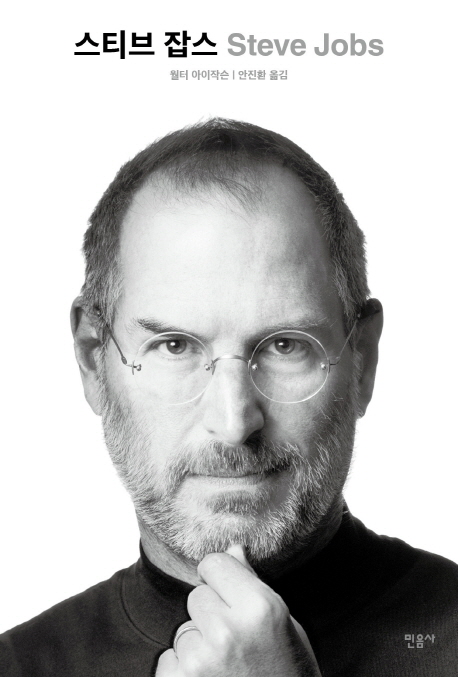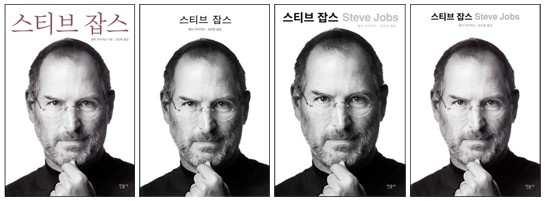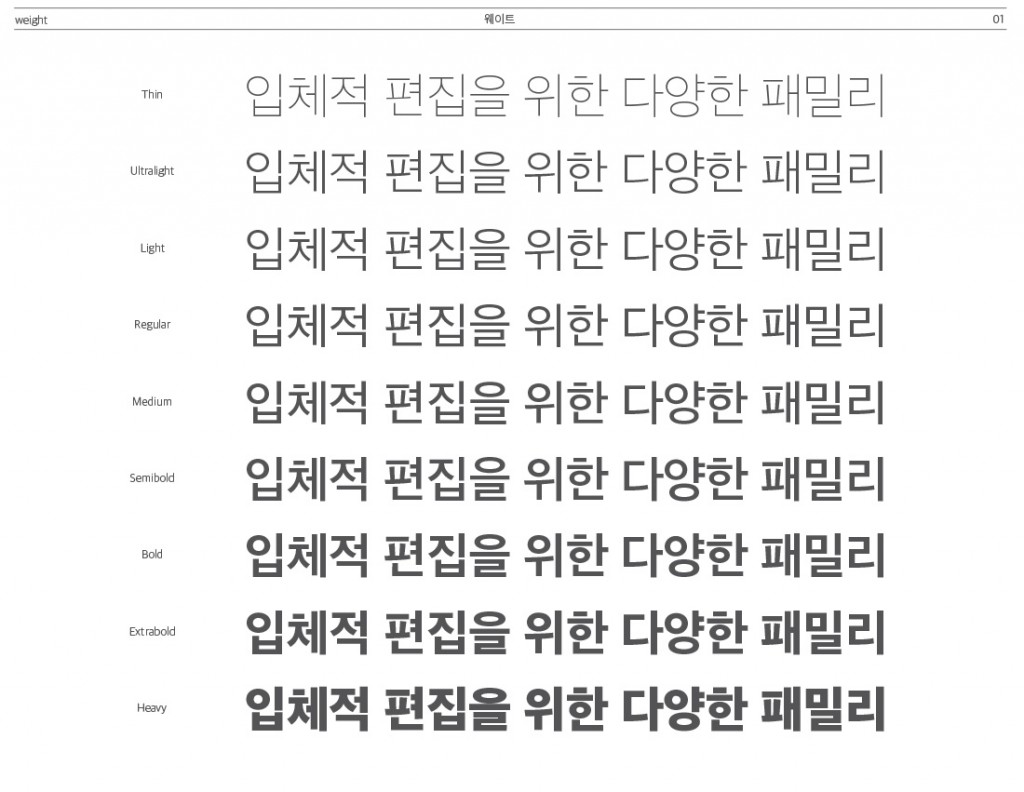
<스티브 잡스> 편집후기 : 스티브 잡스 그리고 산돌고딕Neo
2011년 10월 5일. 전 세계인이 공통으로 기억하는 금세기 몇 안 되는 날짜 중에 하나가 아닐까 싶다. SNS에서, 그리고 전 세계 각지에서 스티브 잡스를 그리워하며 애도했다. 트위터에서는 추모의 글이 넘쳐흘렀고, 애플 매장을 비롯하여 그를 떠올릴 수 있거나 기릴 수 있는 곳이라면 어디든 한 입 베어 문 사과와 추모의 포스트잇이 쌓여 갔다.
“단순함이란 궁극의 정교함이다.”
한국 시각으로 2011년 10월 6일. 그날 아침을 나도 기억한다. 아니, 잊을 수가 없다. 전날 늦게까지 야근을 했던 터라 출근 준비가 평소보다 늦어 서두르던 참이었다. 그런데 들려온 아침 뉴스는……. 쉽게 쓰는 표현으로, 거짓말 같았다. 그전부터 그의 건강이 악화되었다는 소식을 들었고, 여기저기서 우려의 목소리를 들었던 터라 생각지도 못했던 일이라고 할 수는 없었지만, 그럼에도 충분히 급작스러웠고, 그의 팬으로서 충격을 받았다. 순간적으로 멍해지고 슬픔이 몰려왔다.
사실 생각보다 많은 이들이 내게 조심스럽게 물었었다. “만약에 잡스가 책 출간 전에 사망하면 책은 어떻게 될까요?” 한편 잔인하지만 또 한편으로 던질 수밖에 없었던 그들의 질문에 나는 대답할 수 없었다. 그런데 그 결론이 갑자기 저 멀리서 나를 향해 달려오기 시작한 것이다. 팬으로서의 슬픔은 접고, 몇 달 전부터 그의 전기를 준비해 왔던 편집자로서 난 패닉에 빠졌다. 정신을 차리고 그의 마지막 목소리가 담긴 전기를 정말로 잘 내야만 했다.
이미 숨 가쁘게 달려온 터였지만, 많은 이들이 책을 기다리고 있었고 지체할 시간이 없었다. 그리하여 29개국의 편집자가 밤낮 없이 ‘전 세계 동시’에 머리를 쥐어뜯고, 고민하고, 마음을 졸였고, 『스티브 잡스』는 변경된 출간 일자 10월 24일에 마법처럼 ‘전 세계 동시’ 출간되었다.
『스티브 잡스』의 출간 준비를 하면서 가장 고민이 되었던 부분은 잡스도 늘 중요하게 여겼던 디자인이었다. 최종 결과물이 나왔을 때, “바로 이거야!”라는 생각이 들었고 그제야 우리 모두 가슴을 쓸었지만, 의외로 그 고민의 과정은 험난했다.
일단, 『스티브 잡스』가 서점에서 경제경영 분야로 분류될 것이 문제였다. 일반론으로 말할 수는 없지만, 특히 경제경영 분야의 도서 표지들은 대체로 제목이 크고 잘 보이게, 그리고 이미지도 분명하게, 과감한 디자인을 하는 경향이 있다. 그런 시장에서 독자들에게 어필을 하려고 하면서 시장의 법칙을 무시하기란 쉽지 않았다. 담당 디자이너도 스티브 잡스가 추구하는 세련된 감각과 독자에게 분명하게 어필할 수 있는 디자인 사이에서 고민이 많을 수밖에 없었다.
첫 번째 이미지는 우리가 초기에 냈던 시안 중 하나이다. 제목이 분명하게 눈에 띄도록 하는 것이 가장 큰 목적이었다. 하지만 그 목적에만 충실할 뿐, 어딘가 어색하고, 스티브 잡스의 이미지에는 어울리지가 않았다. 그래서 잡스의 정체성을 드러내고자 두 번째 이미지처럼, 당시 애플 제품에서 사용하던 애플고딕체도 시도해 보았지만, 제목이 명확하게 보이지 않아 제목으로 쓰기에는 적당하지 않았다.
제목에 쓰기 좋은 서체를 찾는 것은 쉽지 않았고, 출간일은 점점 다가왔다. 그렇게 애간장이 타던 중 돌파구를 찾기 위해 민음사와 인연이 있던, ㈜산돌커뮤니케이션에 근무하는 서체 디자이너에게 의견을 물었다. 그녀는 마침 애플의 iOS5 베타 6에서 한글 전용 폰트로 채택되었던 폰트가 있다고 했다. 지금은 애플의 정식 한글 서체로 채택되었지만, 당시에는 테스트 중이었던 산돌고딕네오였다. 그녀는 고맙게도 산돌고딕네오로 제목을 잡은 시안을 샘플로 보내 주었다. 위의 세 번째 이미지다. 이 시안을 받았을 때, 우리는 이제야 맞는 길로 들어섰다는 것을 알았다. 편집부에서 서체 자문을 구하고 있을 때, 마침 담당 디자이너도 같은 생각으로 전화를 해 왔으니, 우리는 같은 순간에 정답을 깨달았던 것이다.
네 번째 이미지는 우리가 익히 알고 있는 한국어판 『스티브 잡스』 표지다. 산돌고딕네오 서체를 쓰되 좀 더 세련되게 다듬었다. 어떤 면에서는 파격적인 디자인이었다. 이 정도 책 크기에서 이렇게 제목을 작게 쓰고, 책 뒷면에 카피 한 줄 쓰지 않은 책은 아마 없을 것이다. 하지만 우리는 이 표지 시안을 받아 들었을 때 분명히 깨달았다. 제목을 더 크게 말할 필요도 없고, 이 책이 어떤 책인지 더 설명할 필요도 없다는 것을. 스티브 잡스의 확신에 가득한 얼굴이 모든 것을 분명하게 말하고 있었고, 우리는 가능한 덧붙이지 않도록 애써야 했던 것이다. “단순함이란 궁극의 정교함이다.”라는 잡스의 말이 생각나는 순간이었다.
10월 24일, 한국을 제외한 28개국 다른 출판사에서도 고민의 결과를 공개했다. 아마도 같은 시각 같은 고민을 했을 다른 나라 출판사에서 나온 『스티브 잡스』 표지는 다음과 같았다. 어느 쪽이 좋다 나쁘다 평할 수는 없지만, 우리가 처음 고민했던 것처럼 제목을 분명하게 하려고 애쓴 곳도 있었고, 우리와 비슷한 결론에 도달한 곳도 있었다.
『스티브 잡스』를 편집하고 출간하는 것은 새로운 경험이었다. 그가 IT 업계에서 디자인에 대해 다른 생각을 했듯, 우리도 잡스 덕분에 표지 디자인에 대해 다른 생각을 할 수 있었다. 『스티브 잡스』가 아니었다면, 시도조차 하기 힘든 일이었다.
벌써 1년이 지났다는 것이 믿기지 않는다. 한 번도 만난 적이 없지만, 그의 전기를 몇 번이나 읽으며 그를 마치 알 것만 같은 기분이 드는 것은 나뿐만이 아닐 것이다. 모두와 함께 그의 명복을 빌고 싶다.
산돌고딕Neo
국문 폰트명 Sandoll 고딕Neo1
영문 폰트명 Sandoll GothicNeo1
디자인 디렉팅 권경석
폰트 디자인 권경석, 이도경
웨이트 9종
출시년도 2011년